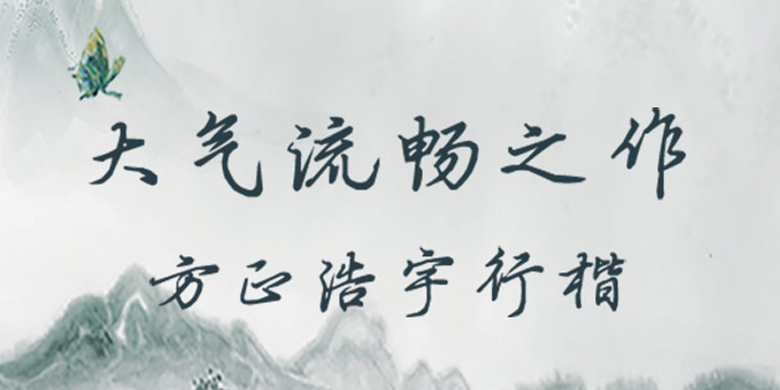
方正手迹-方正浩宇行楷
方正手迹-方正浩宇行楷,这款字体结构工整、笔画清晰,兼顾美观与易读性,适用于标题、正文、海报、包装、LOGO 等多种场景。字形优雅稳定,风格百搭耐看,适配日常排版与创意设计,让文字呈现更舒适、更具质感。方正手迹-方正浩宇行楷一笔一画,皆是细节,以均衡的比例、流畅的线条打造舒适视觉体验,字形端正大气,风格简约现代。无论是商业设计、品牌宣传还是日常排版,都能轻松驾驭,让文字更有格调与力量。方正手迹-方正浩宇行楷字体下载。
字体品牌: 方正手迹 设计师:张森 字体分类:常规书写·硬笔 字体属性:精品字 字符集:大陆简体(GB2312-80) 发布时间: 2020
方正浩宇行楷是一款毛笔书写的传统字体,字体笔画舒展,字形宽博大气,起承转合,笔意连贯,气韵悠远。适用于文艺类的书刊、品牌广告和产品包装设计,现代诗歌、短文排版,影视字幕用字,以及社交网络的个性化用字。